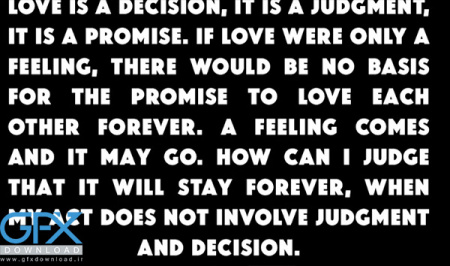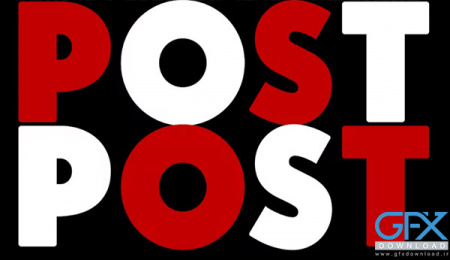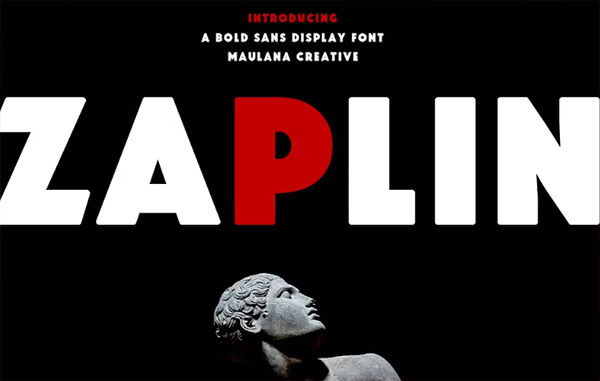
دانلود فونت پررنگ Zaplin
فونت پررنگ Zaplin
دانلود فونت انگلیسی پررنگ Zaplin
Zaplin یک فونت انگلیسی نمایشی با کاراکتر های حروف بزرگ است. با طراحی پررنگ، کاراکتر های قوی. با دانلود فونت پررنگ Zaplin یک کار خلاقانه به شما می دهد. فونت Zaplin از بیش از 100 زبان چند زبانه پشتیبانی می کند. این فونت برای طراحی لوگو، رسانه های اجتماعی، عنوان فیلم، عنوان کتاب، یک متن کوتاه حتی یک حرف متن طولانی و برای فونت متن ثانویه شما با sans یا serif خوب است. شامل زاپلین (WOFF) - زاپلین (TTF) - زاپلین (OTF)